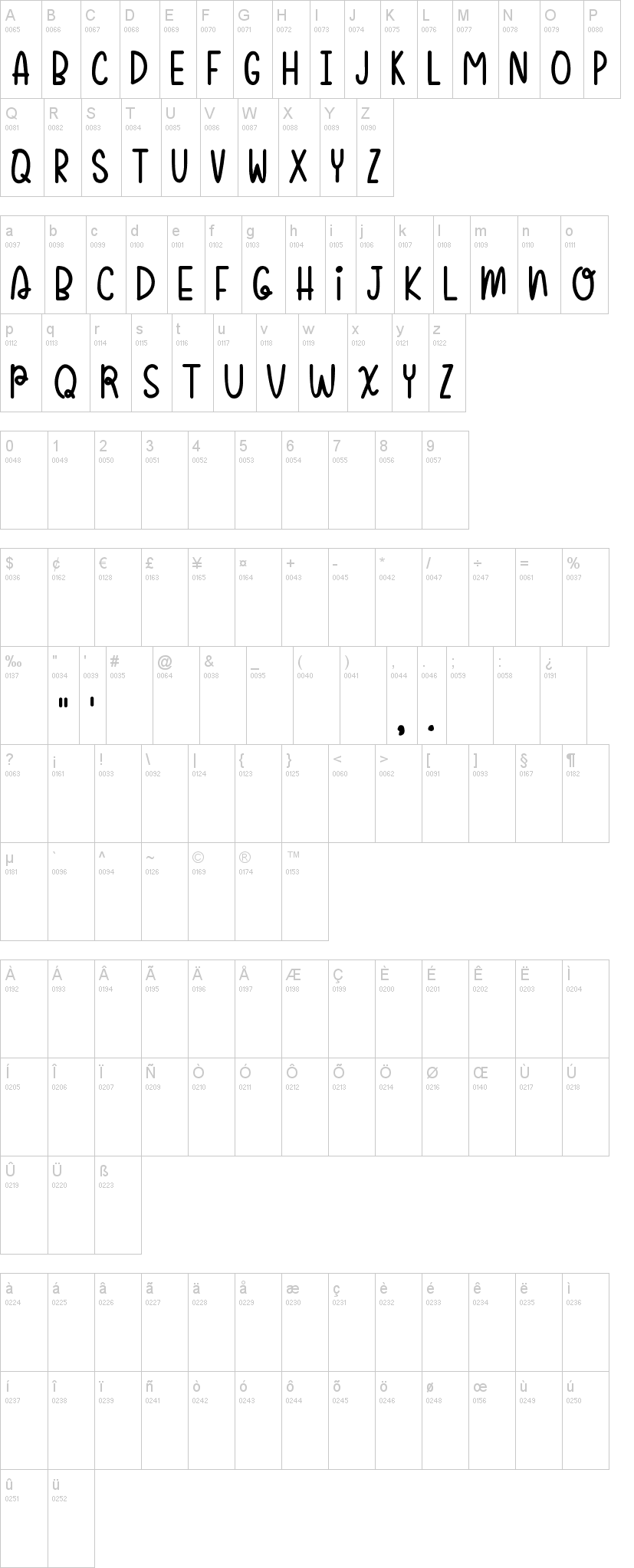
Sugar Poof是一款由Font Diner推出的手写脚本字体,它结合了欧洲和美国的脚本风格,具有柔和的曲线和古典的字形,可以为您的设计带来活力和温暖的感觉。它的特点是可以创造出一种温柔友好的氛围,可以为您的设计增添柔和的色彩,并且可以搭配多种不同的字体,使您的设计更加精致。内容介绍
Sugar Poof是一款非常不错的手写艺术字体,具有很好的视觉感,适合于文化类的宣传设计、商业类品牌的广告和产品包装设计以及个性化文字排版等较多场景。